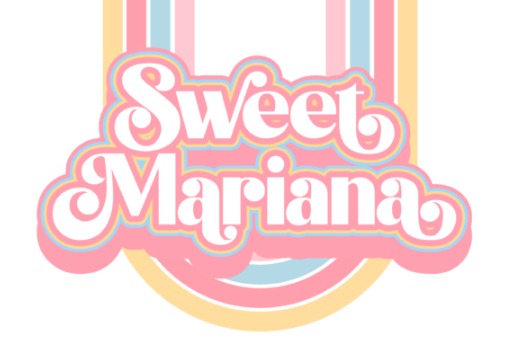
[Creativefabrica] Shining Bright Font (2022)
Shining Bright - красивый и симпатичный шрифт.
Он будет отлично смотреться на заголовках, журналах, логотипах, брендинге и многом другом!
Shining Bright - красивый и симпатичный шрифт.
Он будет отлично смотреться на заголовках, журналах, логотипах, брендинге и многом другом!